Memilih font jersey World Cup 2026 yang tepat adalah salah satu kunci utama agar desain jersey sepak bola terlihat lebih profesional, modern, dan premium. Tren desain jersey bola 2026 kini mengarah ke tampilan yang lebih clean, futuristik, dan sporty. Pemilihan font name set serta nomor punggung menjadi elemen yang tidak boleh diabaikan.
Banyak desain jersey bertema World Cup 2026 kini menggunakan font bergaya futuristik dengan bentuk tegas dan berkarakter kuat. Selain enak dilihat, jenis font seperti ini membuat nomor punggung lebih jelas terbaca, baik di lapangan maupun untuk kebutuhan fashion football sehari-hari. Menurut FIFA, World Cup 2026 akan menjadi edisi dengan jumlah tim terbanyak sepanjang sejarah yang artinya bakal lebih banyak jersey dan lebih banyak peluang desain custom.
Jika kamu sedang mencari inspirasi, berikut 24 rekomendasi font jersey World Cup 2026 yang keren dan cocok untuk custom jersey, produksi brand apparel, hingga bisnis printing profesional.
1. Font Futuristik Sporty: Font Jersey World Cup 2026 Paling Populer
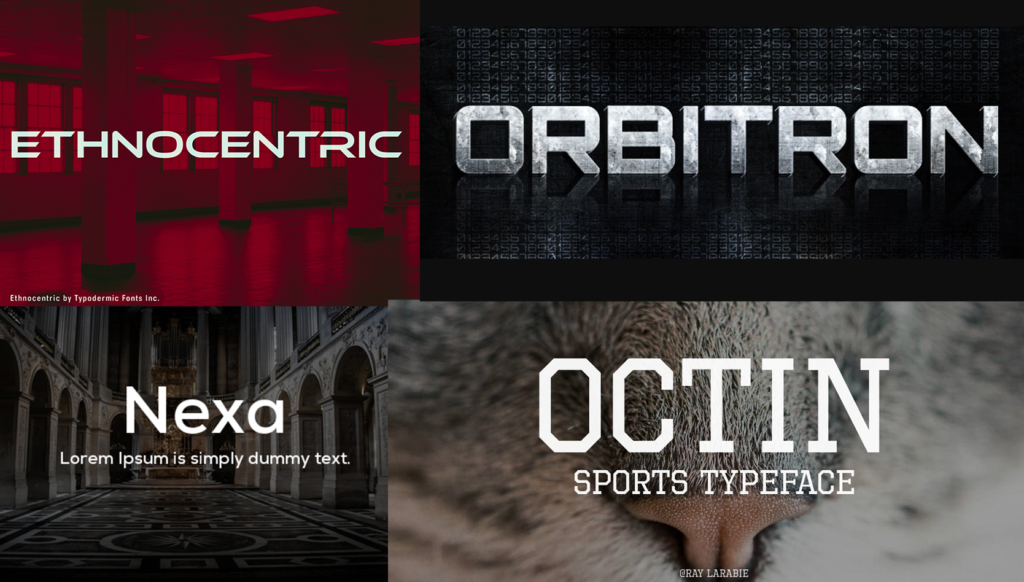
Font futuristik sporty menjadi pilihan nomor satu untuk desain font jersey World Cup 2026 karena karakternya yang tegas, modern, dan mudah dikenali dari jauh.
Ciri khas font futuristik sporty:
- Sudut tajam dan bentuk angka modern
- Terlihat sporty dan agresif
- Tetap clean dan mudah dibaca
- Cocok untuk efek metallic atau glossy
Cocok digunakan pada:
- Jersey tim nasional modern
- Fantasy jersey dan street football jersey
- Jersey komunitas sepak bola
8 Rekomendasi Font Futuristik Sporty untuk Jersey World Cup 2026:
- Ethnocentric
- Octin Sports
- Jersey M54
- Orbitron
- Azonix
- Nexa Bold
- Spartan MB
- Hemi Head
2. Font Bold Minimalis: Font Jersey World Cup 2026 Berkesan Elegan
Selain gaya futuristik, font bold minimalis juga menjadi tren font jersey World Cup 2026 yang banyak diminati. Bentuk huruf yang sederhana dan tegas membuat desain jersey terlihat lebih elegan, modern, dan premium.
Keunggulan font bold minimalis untuk jersey:
- Mudah dibaca dari jarak jauh
- Cocok untuk desain jersey clean dan tidak ramai
- Memberikan kesan modern sekaligus premium
- Fleksibel dipadukan dengan berbagai tema warna
8 Rekomendasi Font Bold Minimalis untuk Font Jersey World Cup 2026:
- Bebas Neue
- Anton
- Montserrat Extra Bold
- League Spartan
- Oswald
- Gotham Bold
- Archivo Black
- Futura Condensed Extra Bold
Style ini sering digunakan pada jersey bertema classic-modern atau luxury football jersey yang ingin tampil mewah tanpa terlihat berlebihan.
3. Font Custom Berkarakter: Font Jersey World Cup 2026 Paling Unik
Beberapa desainer jersey kini mulai menggunakan typography custom untuk menciptakan identitas visual yang lebih unik dan eksklusif menjadikannya pilihan menarik sebagai font jersey World Cup 2026 untuk brand yang ingin tampil beda.
Ciri khas font custom jersey:
- Detail garis sporty yang khas
- Potongan angka dengan karakter tersendiri
- Efek geometric modern
- Tampilan lebih eksklusif dan tidak pasaran
8 Rekomendasi Font Custom untuk Jersey World Cup 2026:
- Varsity Team
- College Block
- Super Brigade
- Badaboom Sport
- Thunderbolt
- Sportypo Regular
- Jersey Sharp
- Attack Graffiti
Jenis font custom ini sangat cocok untuk custom name set agar jersey terlihat lebih personal dan jauh berbeda dari desain pasaran. Baca juga: Cara Mudah Menempatkan Desain di Jersey atau Kaos
4. Material Printing yang Tepat Agar Font Jersey World Cup 2026 Tampil Maksimal
Desain font jersey World Cup 2026 yang keren tidak akan tampil optimal jika hasil print kurang tajam atau mudah rusak. Karena itu, pemilihan material printing menjadi faktor yang sama pentingnya dengan pemilihan font itu sendiri.
Material printing yang tepat menghasilkan:
- Warna lebih nyata dan akurat sesuai desain
- Detail font lebih tajam hingga ke sudut-sudut kecil
- Hasil print lebih awet dan tidak mudah pudar
- Tampilan jersey lebih premium secara keseluruhan